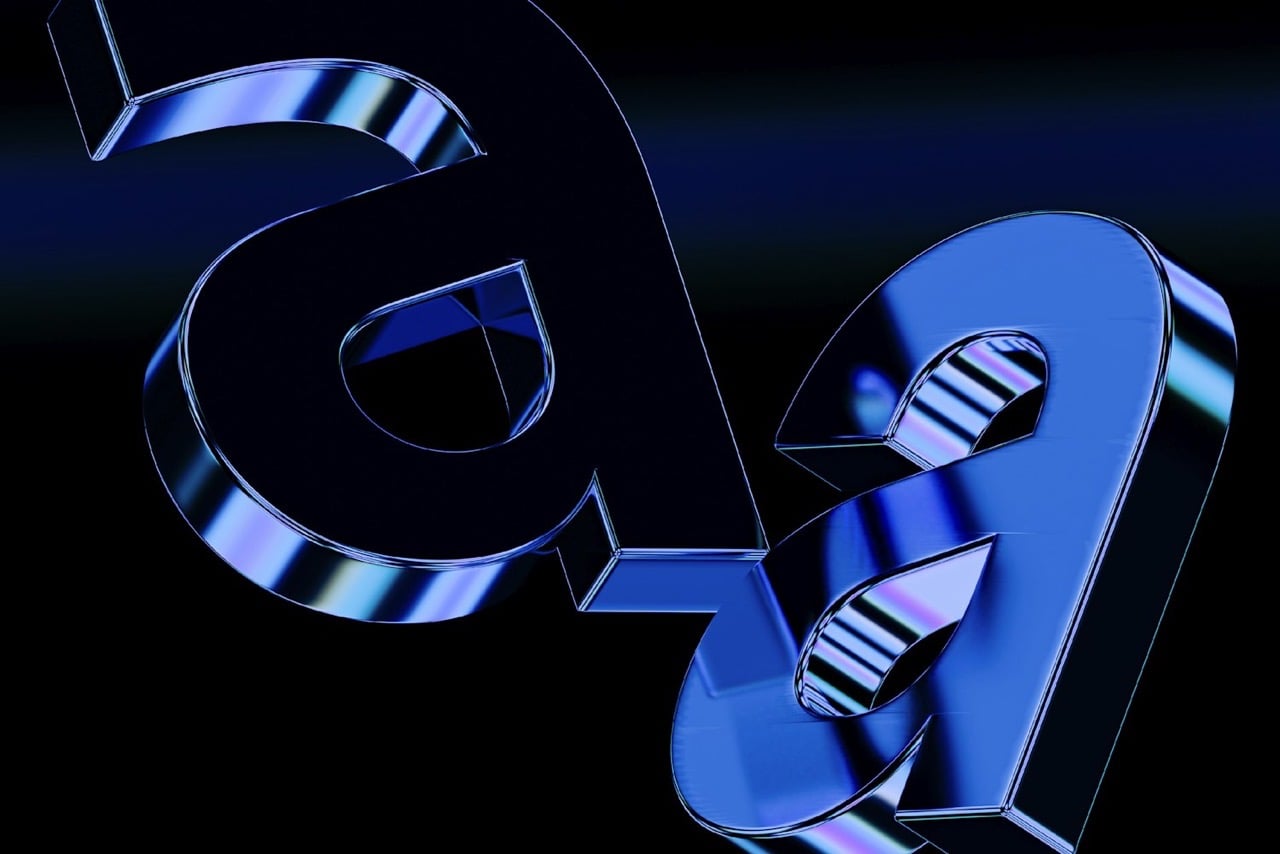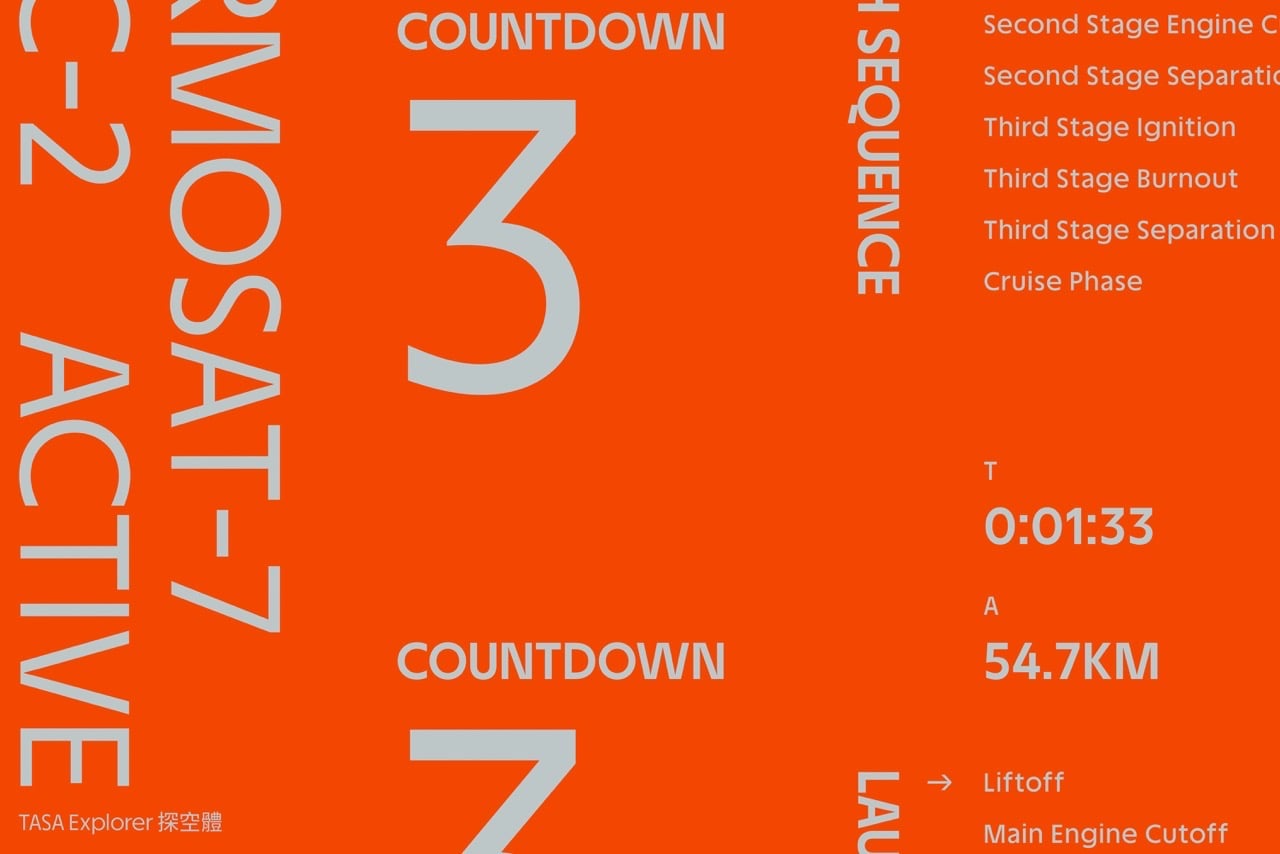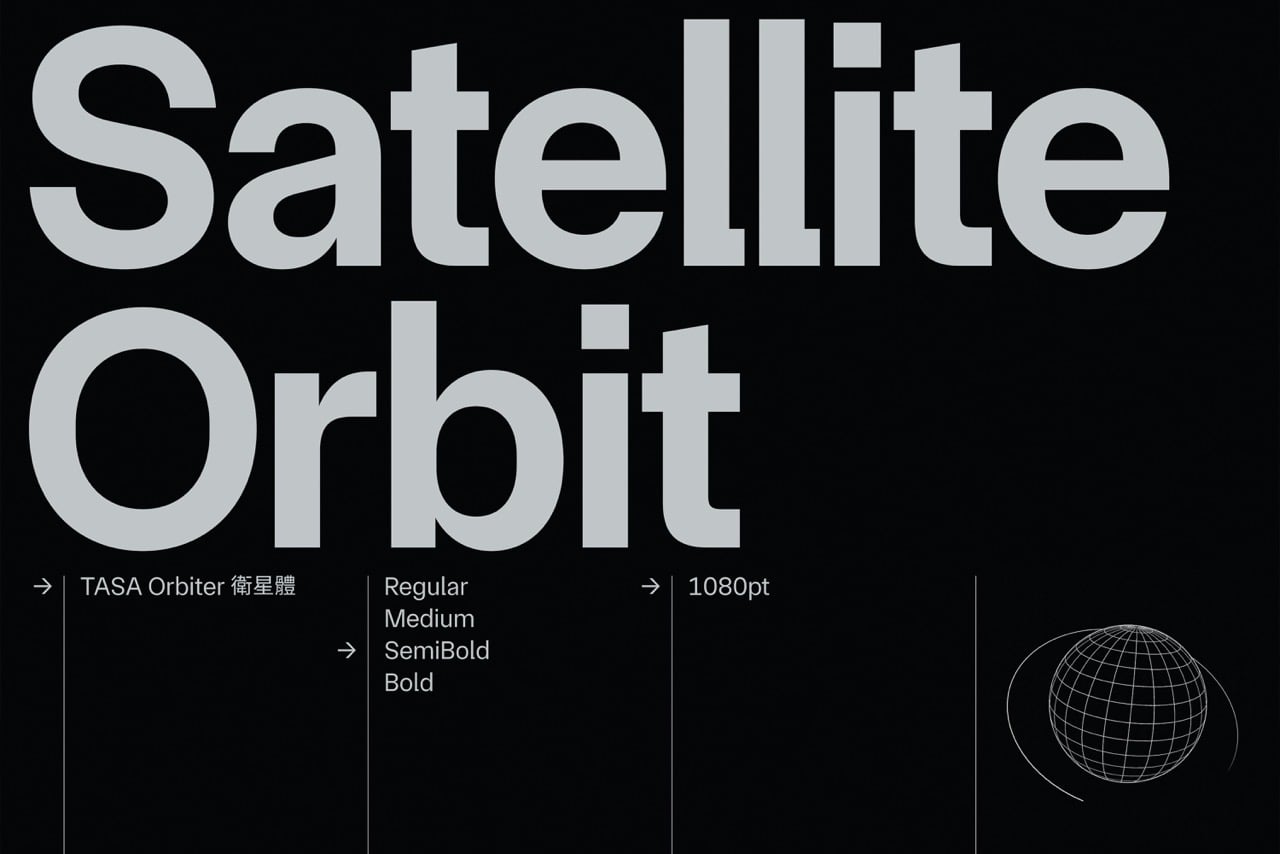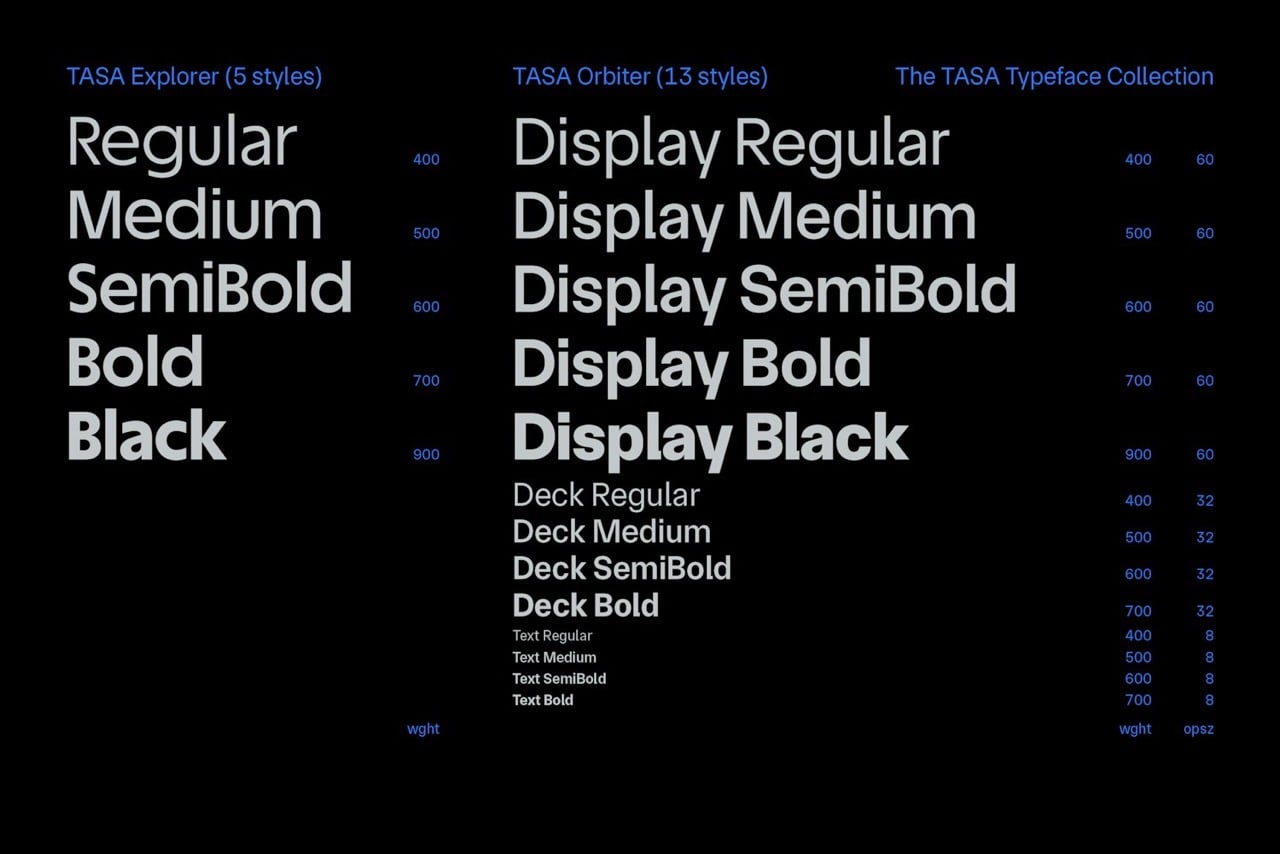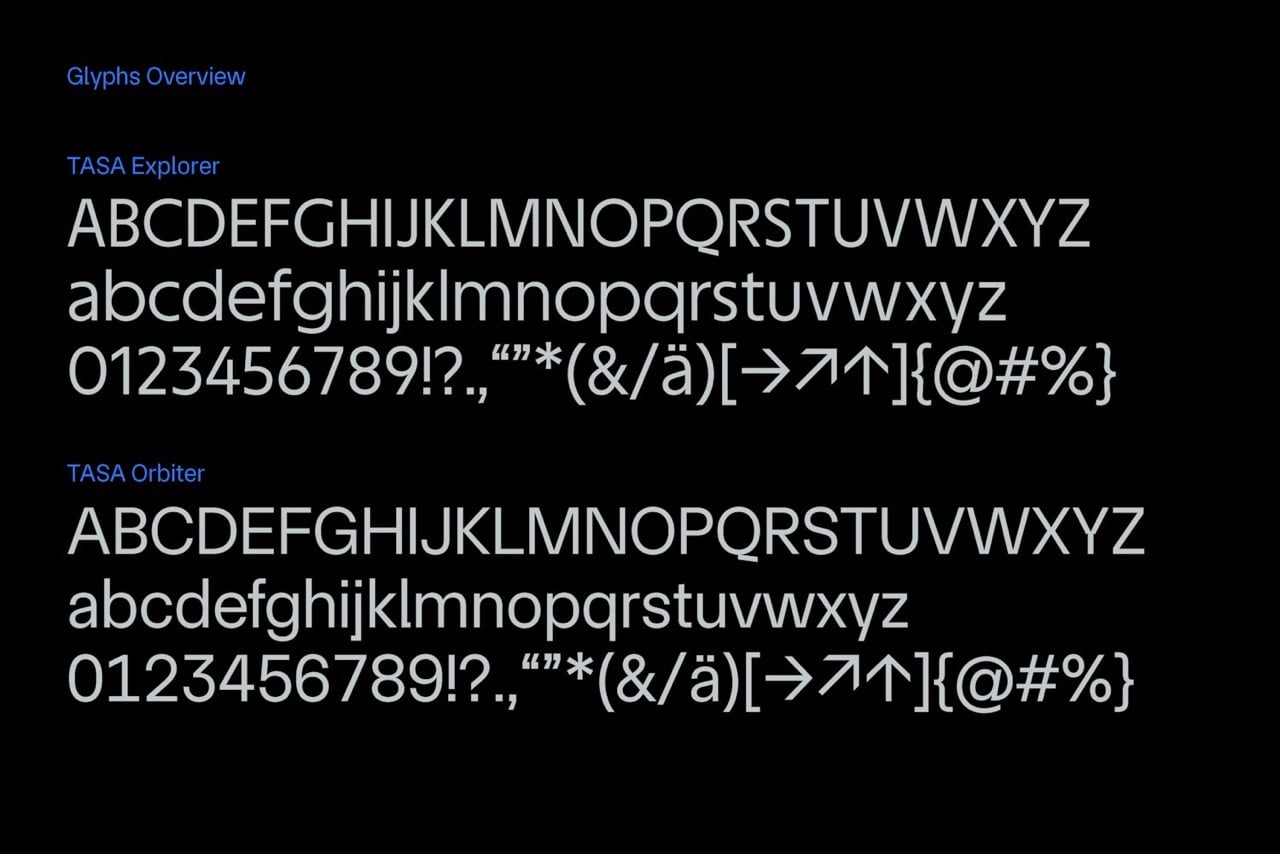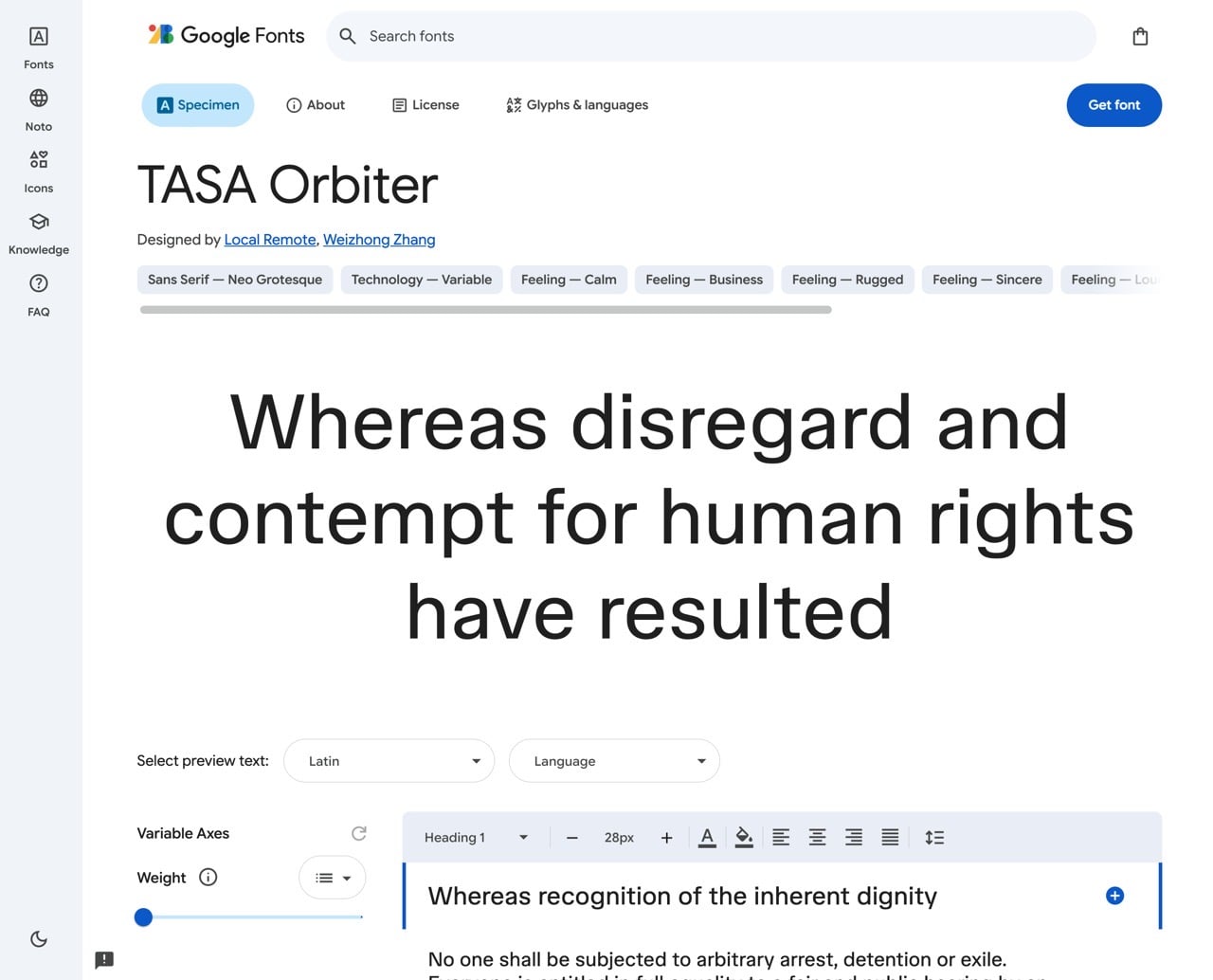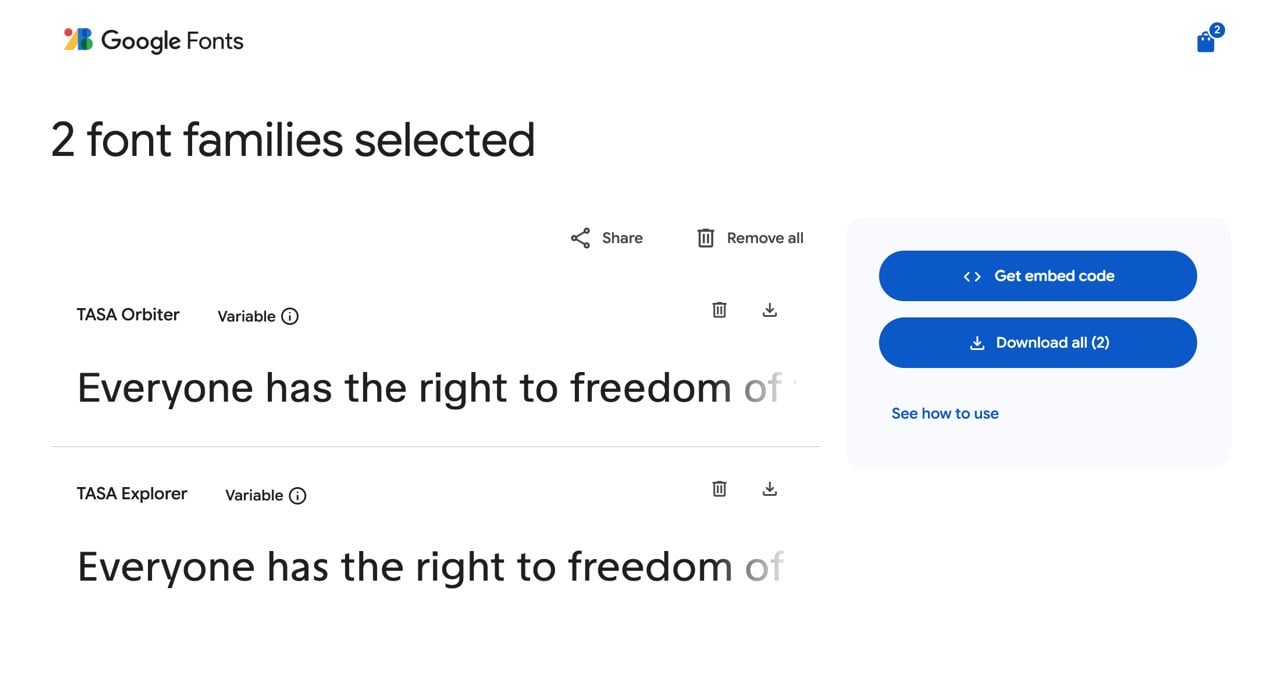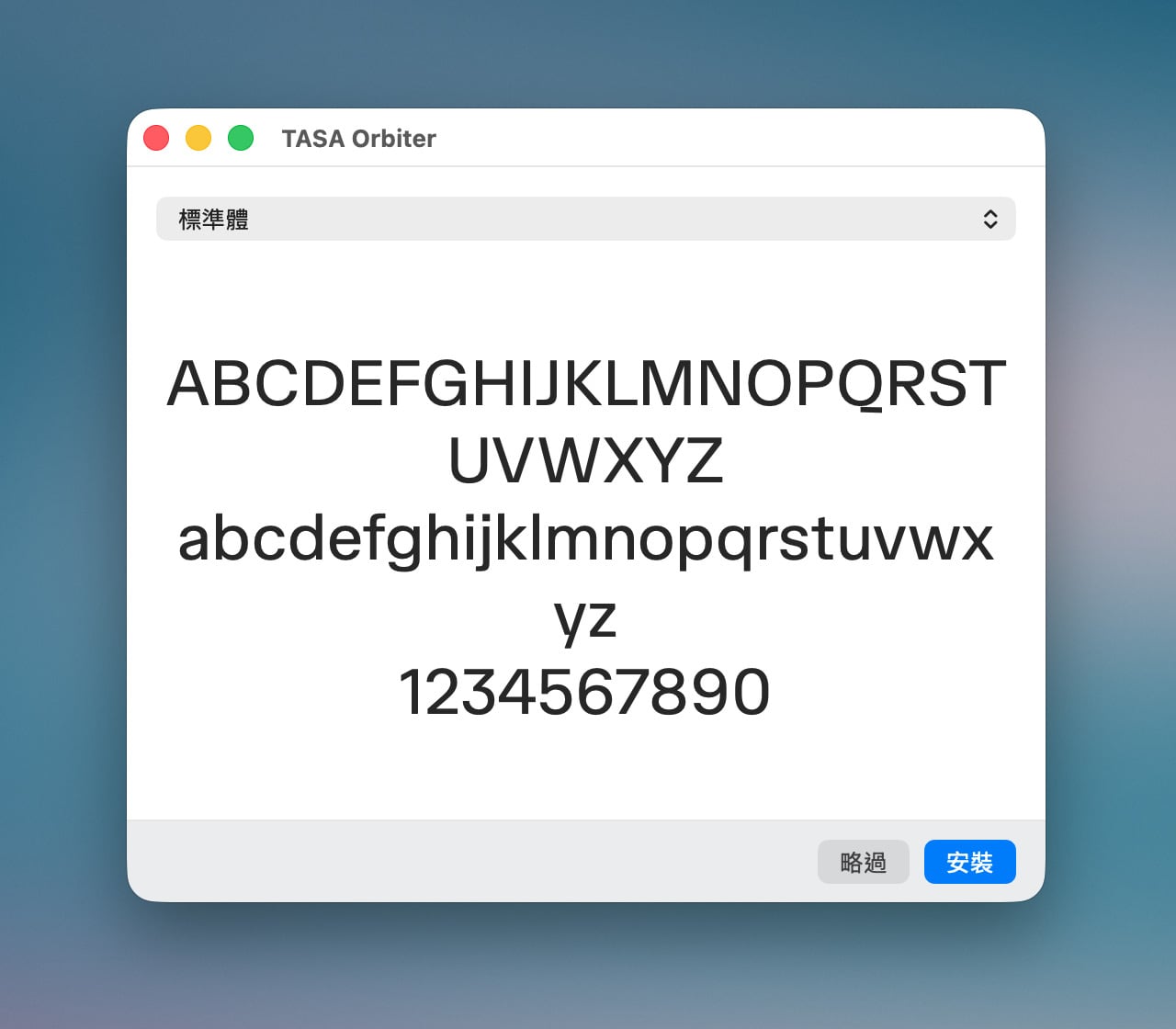
本文重點:台灣國家太空中心推出的開源歐文字型 TASA Explorer 與 TASA Orbiter 成功登上 Google Fonts 平台,成為首款台灣製作的入選字型。採用 SIL 開源授權,提供五種字重與可變式字型格式,不僅支援台語羅馬字,更開放任何人免費下載,廣泛適用於個人及商業專案設計。
台灣首款登上 Google Fonts 的歐文字型
2023 年台灣國家太空中心(Taiwan Space Agency,縮寫 TASA)進行品牌重塑計畫時,委託設計公司 Local Remote(本地遙控)設計兩款全新字型,分別為 TASA Explorer 和 TASA Orbiter,以 SIL 開源字型授權發布,任何人皆可免費下載並應用於個人或商業專案。
今年四月兩款字型達到新里程碑——成功登上 Google Fonts,成為第一個由台灣製作、登上 Google Fonts 網站的歐文字型。全世界使用者都能在 Google 平台自由使用,或將字型檔下載到電腦安裝,使用在各種設計、開發專案。
兩款 TASA 字型特色介紹
TASA Explorer 探空體
TASA Explorer(探空體)是一款幾何無襯線字型,設計語言呼應太空探索精神。特徵包含垂直切割的末端與銳角設計,粗細對比自然。最新版本調整了 x 字高與字母間隔,同時適合標題與內文排版。
TASA Orbiter 衛星體
TASA Orbiter(衛星體)屬於新無襯線體(Neo grotesque),也就是傳統無襯線體(Grotesque)的現代改良版,強調技術操作的精準度。具備偏方形的字腔與直角轉折。第二版將其整合為 5 種字重,提升跨版面的通用性。特點是微方形的字腔與直角的轉折設計,排版效果非常工整,適合使用在內文。